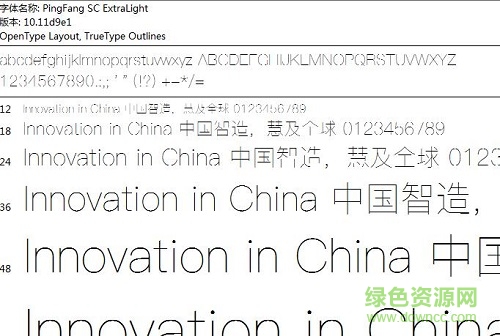
蘋方特細(xì)體是蘋果為中國用戶打造的細(xì)體字體,超細(xì)線狀字體給人非常清秀舒服的感覺,讓整個界面看上去更加的清爽想,喜歡的朋友歡迎下載使用!
蘋方特細(xì)體是蘋果公司打造的一款特細(xì)中文字體,這款字體最大的特色就是跟他的名字一樣寫出來的字非常細(xì),非常適合正文的書寫!